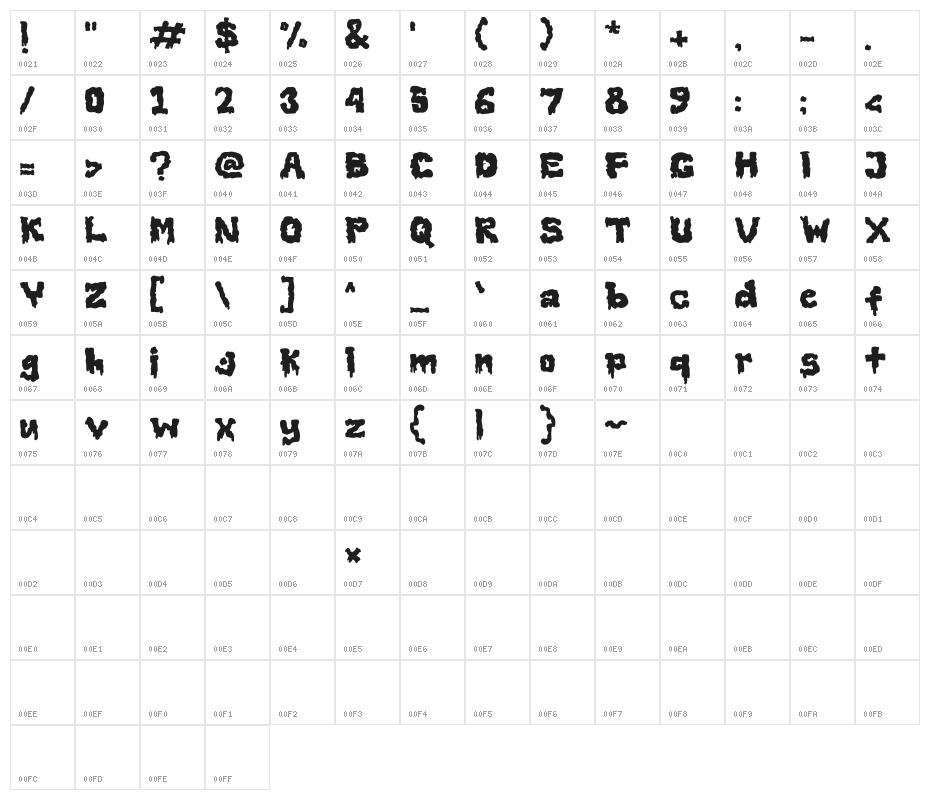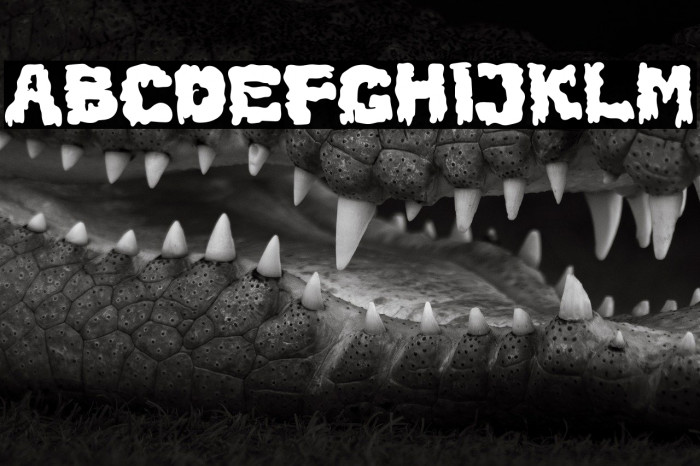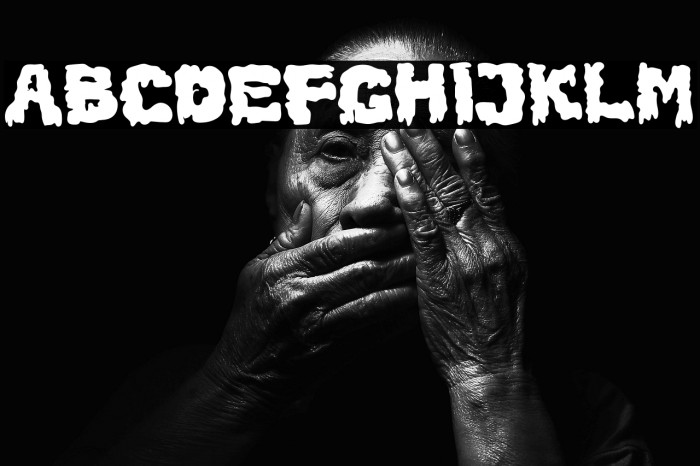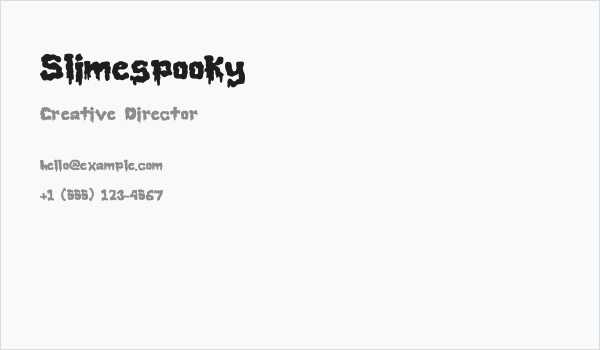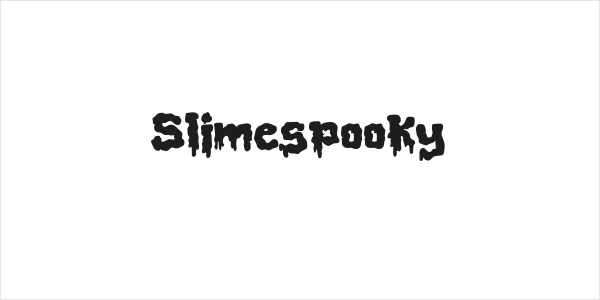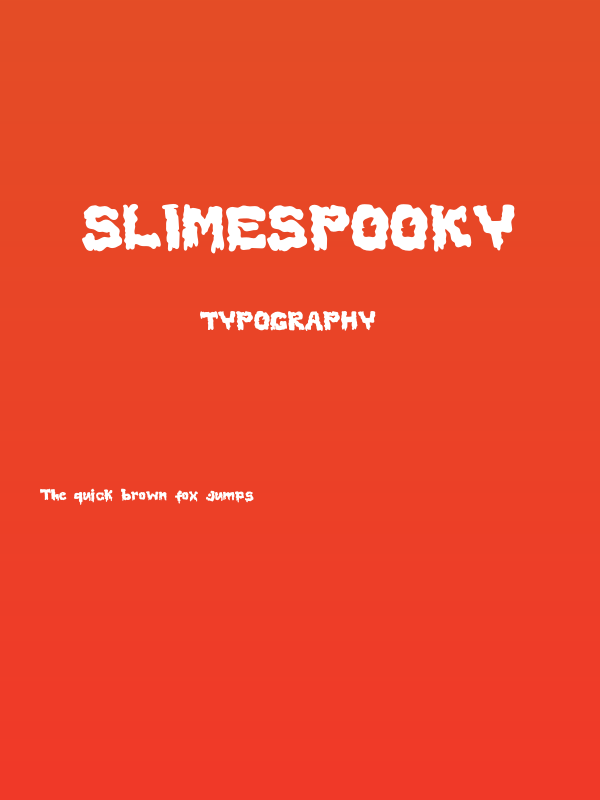
Slimespooky Font
| Caso d'uso | Headlines, Posters, Themed Events |
| Progetti proposti | Perfect for Halloween invitations, horror movie posters, themed party decorations, or any project needing a spooky, playful touch. |